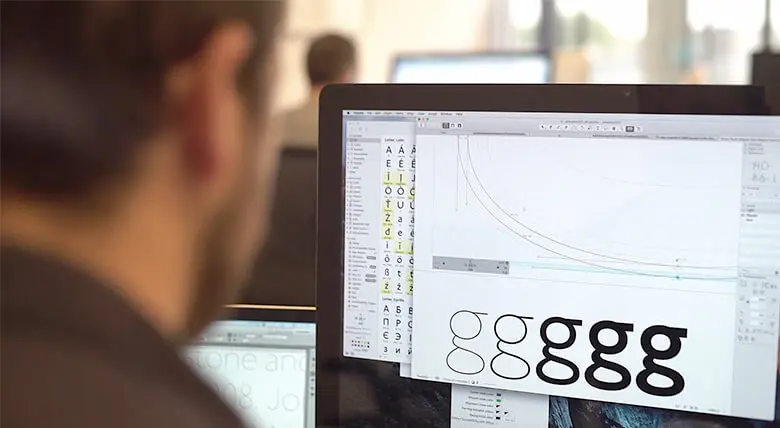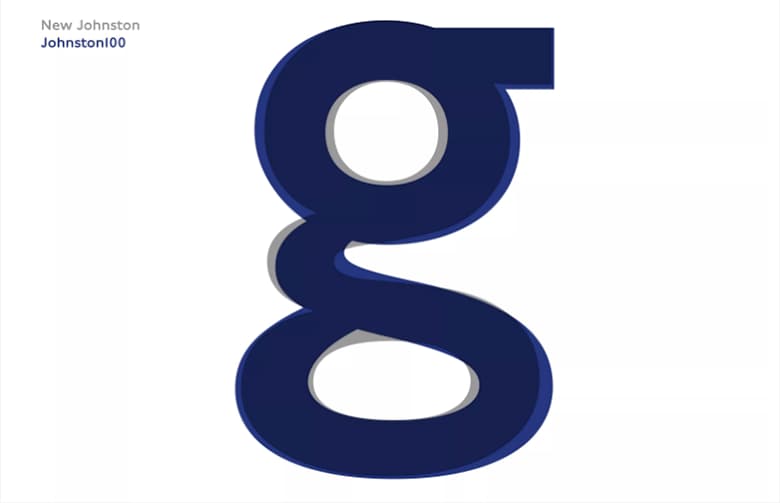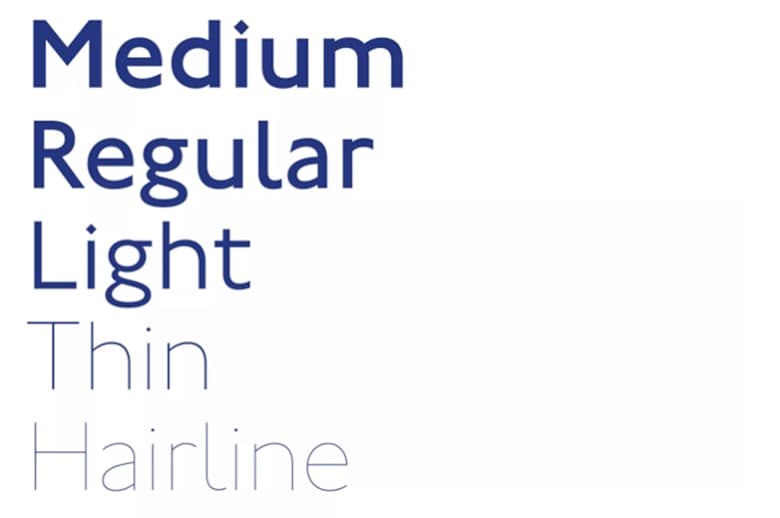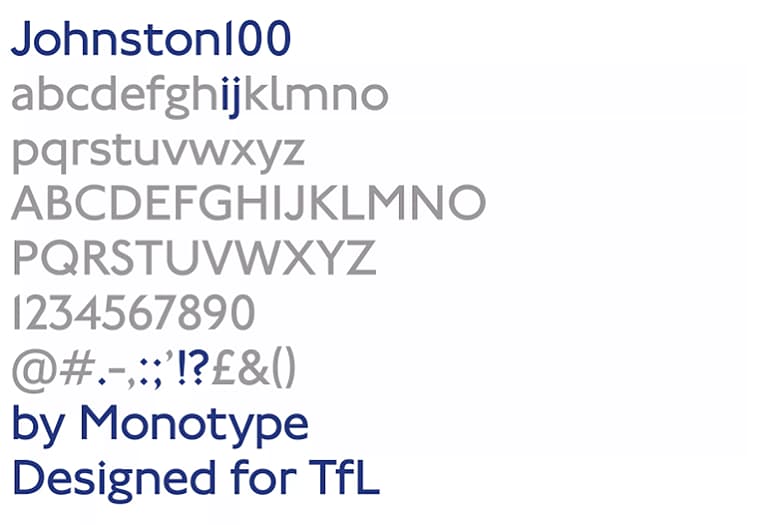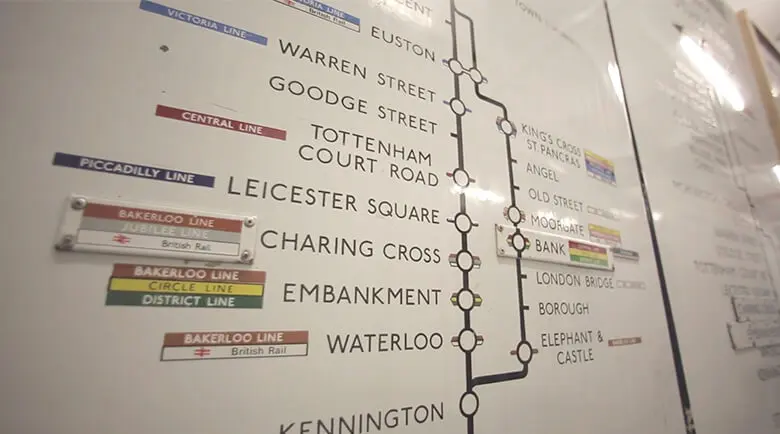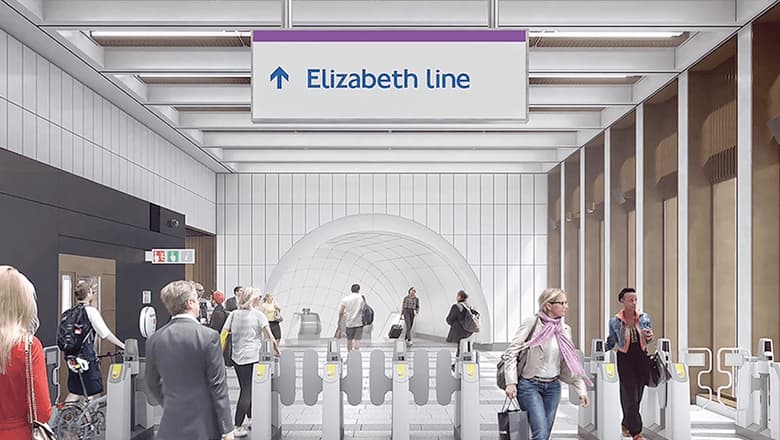
ロンドン市内のすべての地下鉄や電車、バス、駅の看板など、いたるところで使用されている象徴的なフォント「Johnston」。誕生してから100周年の節目の今年、デザインが変更されます。
愛されてきた書体
Johnstonは、1916年にエドワード・ジョンストンさんによってつくられたサンセリフ体の書体です。
可読性が高く整然としていながらも、小文字の“i”や“j”の点がダイヤモンド型をしているなど、遊び心ある親しみやすい書体のため、長年多くの人びとに愛されてきました。
「Johnston100」の特徴
これまでにも1度、Johnstonはリデザインされたことがあります。
1979年、活版から写真植字への移行期に日本人デザイナーの河野 英一さんにより、実用的・均一的にリデザインされ「New Johnston」という書体が誕生しました。
引用元:「Introducing Johnston100 for TfL」 公式動画今回は、書体の汎用性を高めるためにMonotypeが改訂を手掛け、オリジナルであるJohnstonの持つ“味”や“クセ”を取り戻す形で、新書体「Johnston100」がつくられました。
小文字の“g”の斜めに湾曲した部分や、幅を広めに取った“U”など、New Johnstonではなくなっていたディテールが復活しているほか、オリジナル書体をベースに、現代のタイポグラフィの動向やデジタルフォントの必要条件を満たすようリデザインされています。
用意されたウェイトははMedium/Regular/Light/Thin/Hairlineの5種類。
Johnstonは線が太いため、これまでは文字サイズが小さい場合に読みづらいという問題がありましたが、Johnston100では新たに「Thin」「Hairline」の2ウェイトが加わったことで、スマートフォンやPC画面上での可読性を高めています。
また、「@」や「#」など、Web上での使用頻度の高いこれまでになかった文字も追加されました。
時代を反映
地下鉄路線図からモバイルアプリまで、ロンドンの交通システムの拡大に対応できるようリデザインされたJohnston100。
今後2016年7月から地下鉄路線図やポスターなどの印刷物を中心に徐々に展開し、2018年開通予定のクロスレール「エリザベス・ライン」を含む、列車や駅の看板などにも使用される予定です。
時代の変化とともにフォントに求められるニーズが変わるという、わかりやすい例と言えます。
古きを壊し新しきを次々に生み出すのではなく、今回のようにオリジナルへの高い尊敬を持ったリデザインは、“良いデザインとは何か”を改めて見つめなおす良いきっかけになりそうですね。